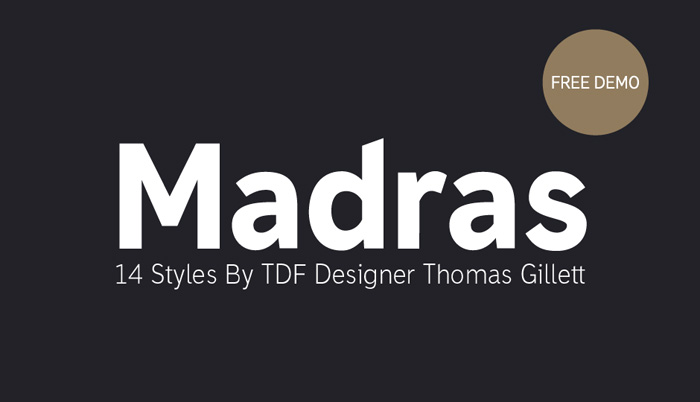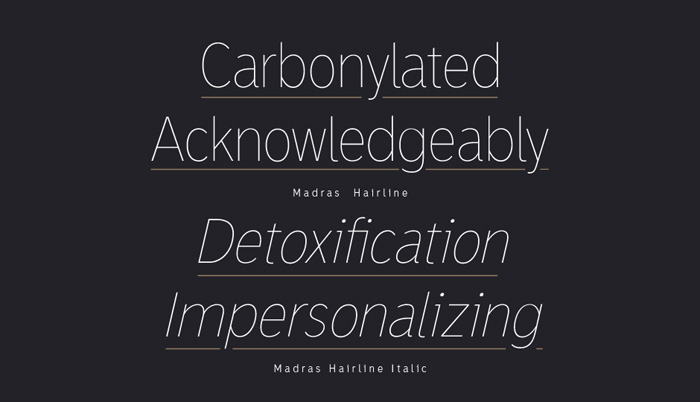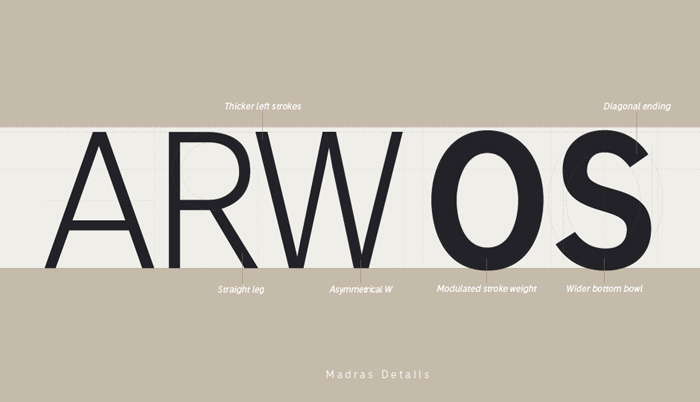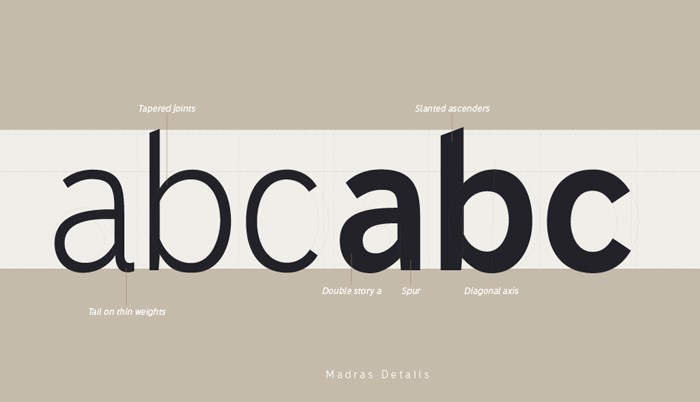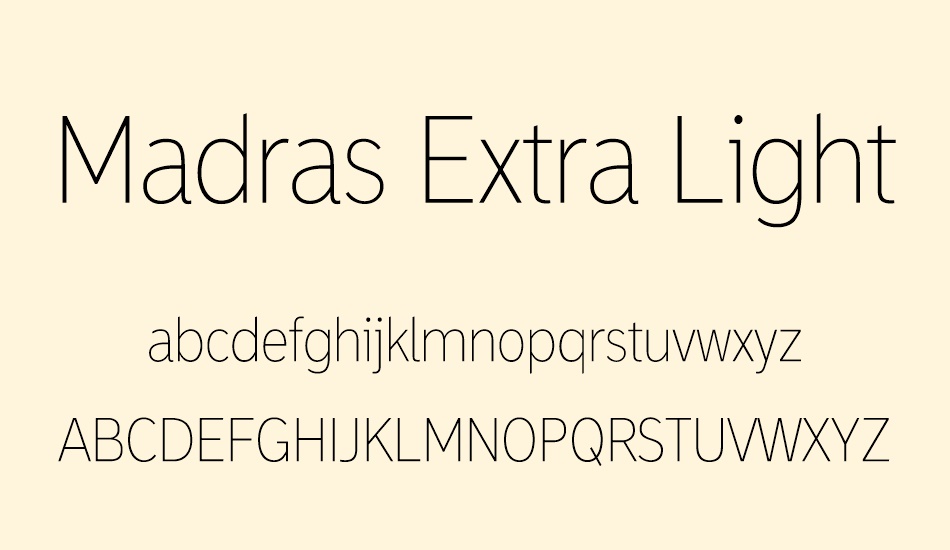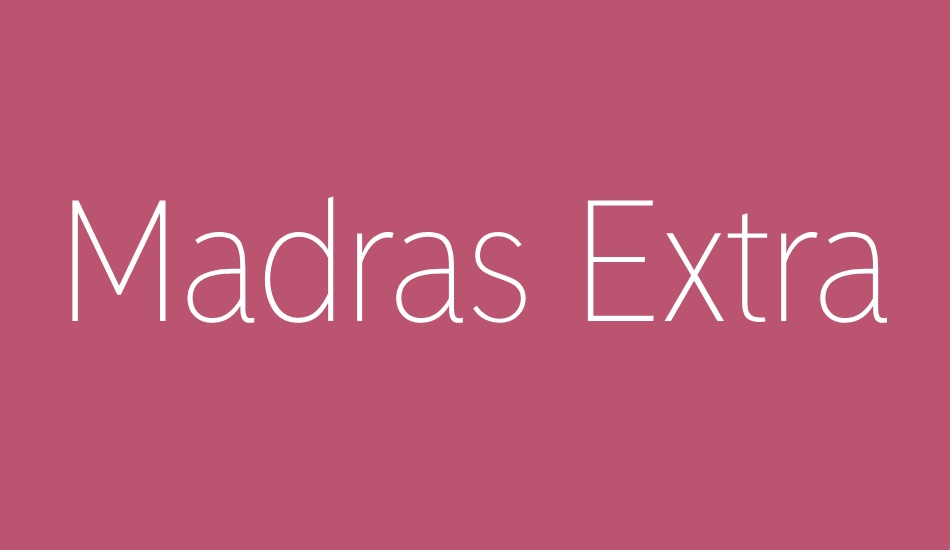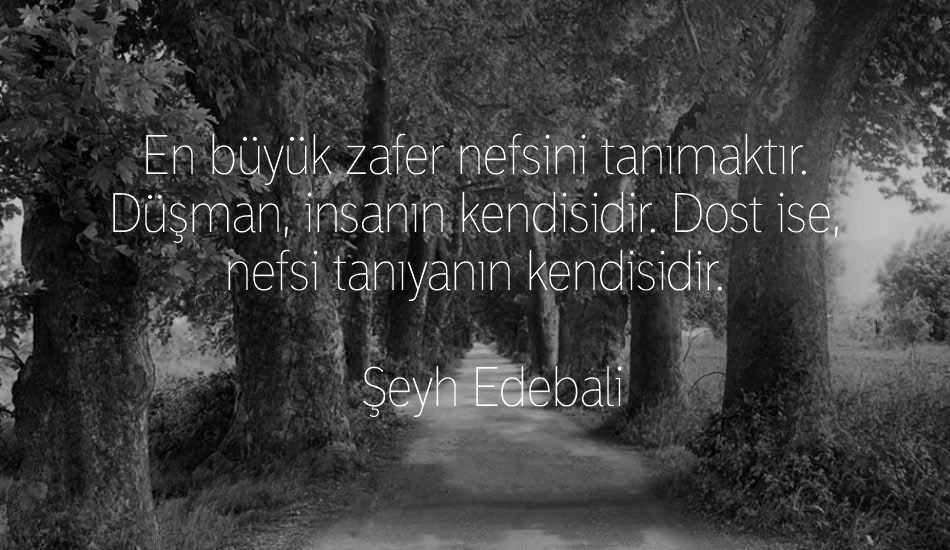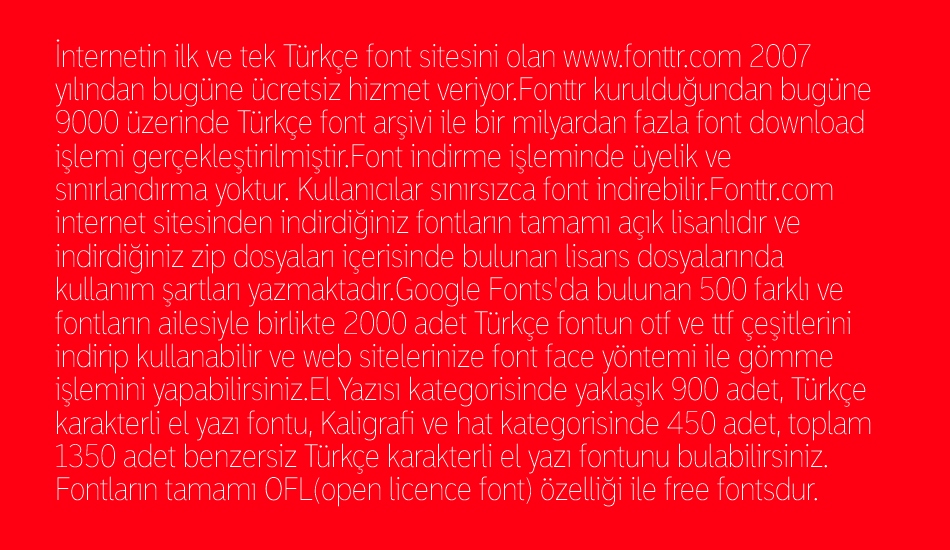
Tasarım ve üretim Thomas'ın Andromeda yazı karakteriyle başlayan ve sokak ve yol kenarı tabelasından ilham alarak 2 sene boyunca yayılmış. Yazı tipi, alan açısından verimli, okunaklı ve sonuçta zarif olacak şekilde tasarlanmıştır. Madras, Helvetica gibi yazım biçimlerinin sadeliğini sunar ve her duruma uygulanabilecek hibrid bir yazı oluşturmak için Interstate gibi yazı biçimlerinin modern tanımlayıcı özellikleri ile birleştirilir.
Madras adı, Twitter'da koştuğumuz bir yarışmadan seçildi. Madras, yazı karakterinin ilhamıyla doğrudan ilgili olan TDF genel merkezinde bulunan caddedir.